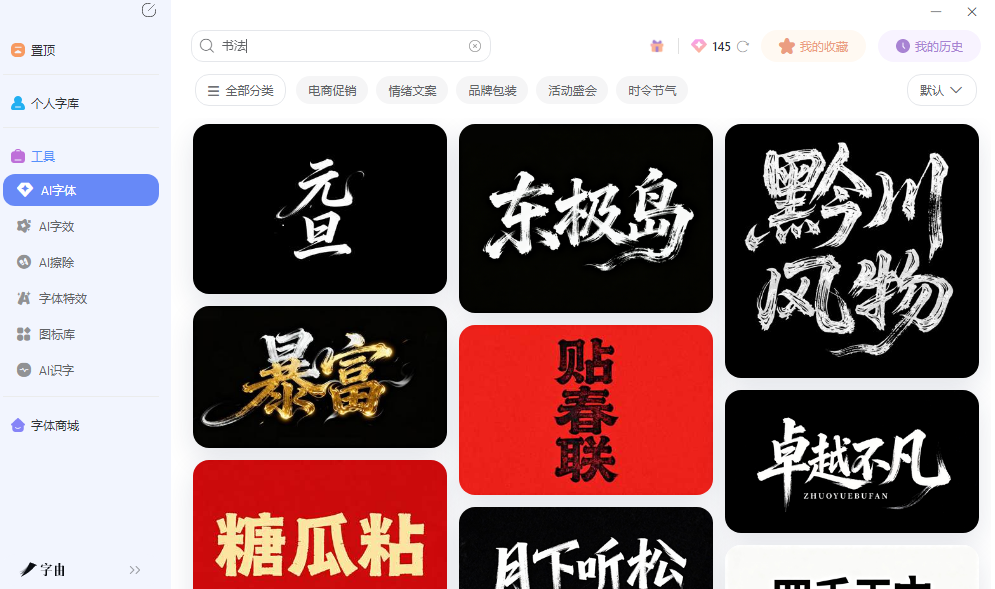
做海报缺书法字?毛笔字生成器直接收藏
做海报、做春联、做红包封面,标题字用黑体宋体总差点意思。毛笔字有年味,有文化底蕴,但自己不会写,去字体站搜"书法体",出来的结果要么笔锋太假像打印的,要么授权不清不敢商用。其实现在有不少毛笔字生成器,输入文案直接出图,行书楷书隶书随便选,生成的PNG透明背景直接拖进设计稿。这篇文章整理的五个渠道,从传统碑帖到现代特效都有,帮你快速搞定春节物料的书法标题。
字由处理书法体需求的方式比较灵活。字体库里书法体是单独分类的,和手写体区分开来。书法体偏向传统书体的数字化再现,行书、楷书、隶书、草书都有覆盖。找的时候先点书法体分类,再勾选免费商用标签,结果列表里就是全部允许商业使用的书法资源。
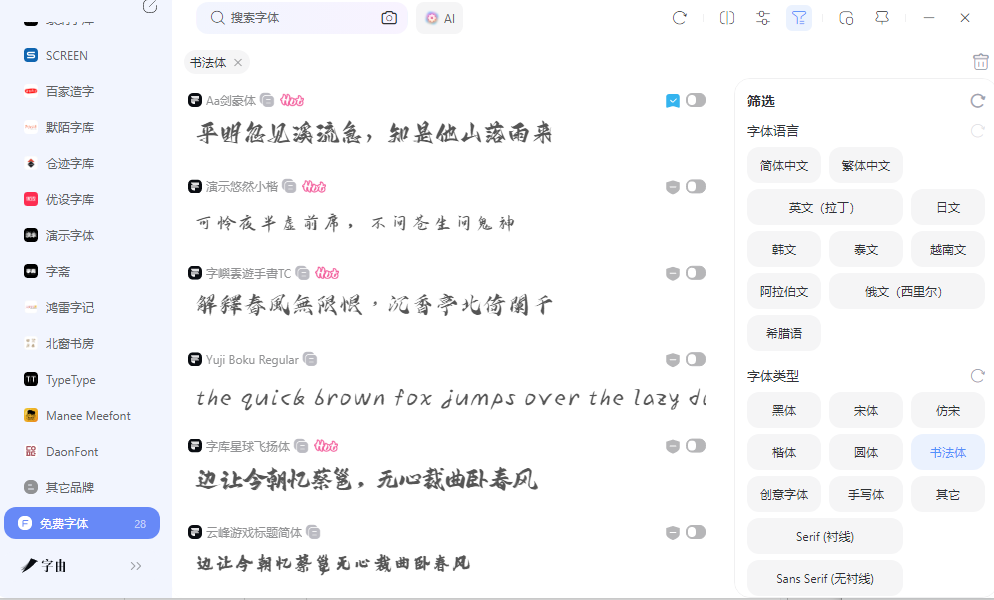
预览框对书法体尤其重要。同样的书法字体,输入"春风得意"和输入"科技未来",气质可能完全不同。有些书法体适合诗词歌赋的优雅语境,有些则适合品牌标语的现代排版。预览支持输入自己的文案,调整字号后观察笔画在不同大小下的清晰度,有些字体放大后飞白效果很明显,有些则显得单薄。确认效果后再激活,避免了装完发现不合适再卸载的反复操作。
对于需要书法效果但不是字体文件本身的场景,字由的AI字体功能可以直接生成带特效的书法字图片。模板库里有不少书法风格的特效模板,水墨渲染、鎏金质感、毛笔飞白等方向都有覆盖。选一个模板,把自己的文案替换进去,大约二十多秒生成一张透明背景的PNG图片,可以直接拖进海报或者电商详情页里做标题。这种方式比找书法体再自己调效果要快不少,尤其适合时间紧、需要快速出方案的情况。
2、艺术字网
艺术字网是一个在线艺术字和书法字转换平台。输入文字后,系统会转换为多种艺术字体样式,其中包括不少书法风格。网站上的书法风格偏向装饰化处理,有些模板在传统书体基础上增加了现代设计元素,比如立体效果、金属质感、霓虹发光等。
作为毛笔字生成器的渠道,艺术字网的优势在于风格多样化,既有传统书法韵味,又有现代创意变体。对于想做春节海报但又不希望过于古典的项目来说,这里的创意书法风格比较匹配。比如传统行书加上金色描边效果,或者楷书加上立体浮雕质感,既有书法的文化感又有节日的喜庆感。生成的图片可以直接下载,流程简洁。网站上还提供了多种预设模板,点击即可切换,不需要手动调参数。
3、阿酷字体
阿酷字体是一个在线艺术字生成平台,支持多种书法风格转换。输入文字后,可以选择行书、楷书、隶书、草书等多种书体风格,系统会生成对应的书法字图片。网站上还提供了多种特效选项,比如描边、阴影、渐变等,可以进一步美化生成的书法字。
作为毛笔字生成器的渠道,阿酷字体的优势在于书体分类比较传统,覆盖了主流书法类型。生成的图片可以直接下载使用,也可以复制到剪贴板粘贴到其他地方。对于需要快速获得正统书法效果、且不需要安装字体文件的用户来说,这里的操作流程比较顺畅。网站还支持调整字号和颜色,可以微调效果以匹配具体需求。
4、第一字体网
第一字体网是一个在线字体转换平台,支持把输入的文字转换为多种书法字体风格。网站上提供了行书、楷书、隶书、草书等多种书体选择,用户输入文案后选择喜欢的书体,系统会生成对应的书法字图片。
这个工具对需要快速获得书法效果的用户比较友好。操作流程简洁,输入文字、选择书体、生成图片,三步完成。生成的图片可以直接下载使用,也可以复制到剪贴板粘贴到其他地方。作为毛笔字生成器的渠道,第一字体网的优势在于书体分类比较传统,覆盖了主流书法类型,适合需要正统书法风格的场景。网站上还提供了字体大小和颜色调节选项,可以微调效果以匹配具体需求。
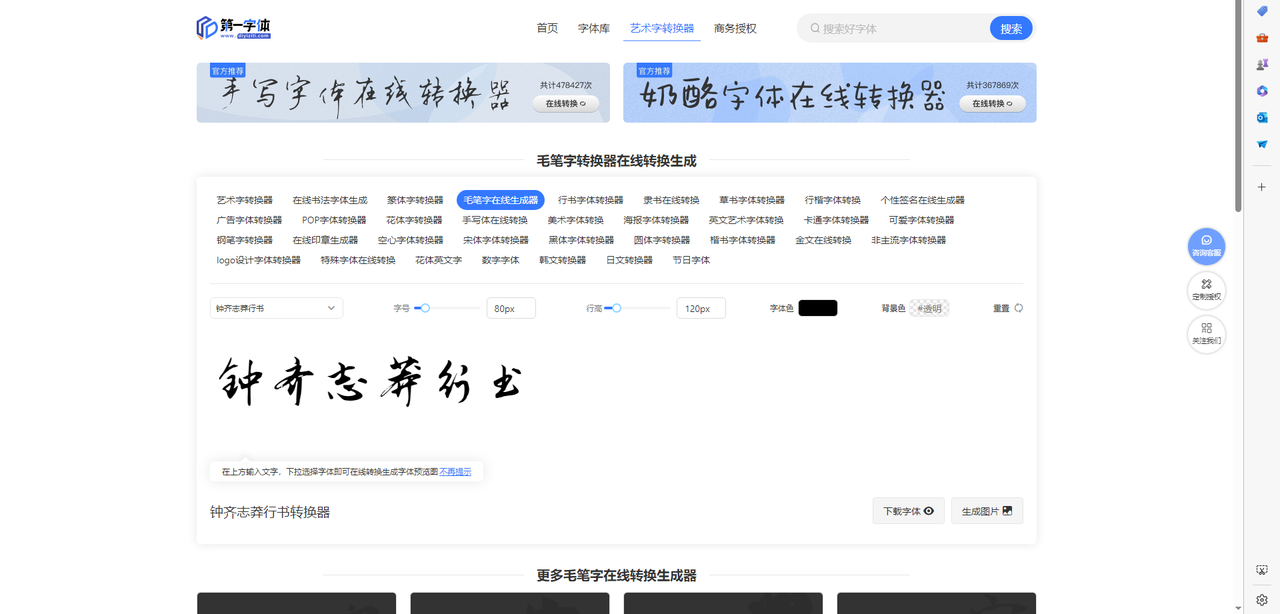
5、书法字典
书法字典是一个专注书法学习和临摹的平台,核心功能是展示历代名家碑帖的高清图片。网站上收录了大量经典碑帖,包括王羲之、颜真卿、柳公权等名家的代表作,每幅碑帖都支持高清放大查看笔画细节。
对于需要毛笔字生成器的用户来说,这个平台的实用价值在于可以直接从碑帖中找到想要的字形。输入一个汉字,系统会在碑帖库中搜索对应的写法,展示出不同名家对这个字的处理方式。想做"龙"字的春节海报标题,可以看到王羲之的行书、颜真卿的楷书、怀素的草书分别是怎么写的,选择最接近项目气质的那一款。作为毛笔字生成器的辅助渠道,书法字典在字形的权威性和多样性方面比较突出,适合对书法品质有较高要求的项目。
做春节海报或者文创包装,书法字体的获取方式取决于使用频率和项目需求。偶尔需要做几张标题图,字由的AI字体生成透明背景PNG,不用安装大体积字体文件,配合每日免费额度成本比较可控,作为毛笔字生成器的主力渠道比较实用。书法字典的碑帖库适合对字形权威性有要求的项目。第一字体网的传统书体覆盖比较全。阿酷字体的操作流程比较顺畅。艺术字网的创意变体适合现代节日氛围。按项目的书法品质要求和风格方向来选就行。